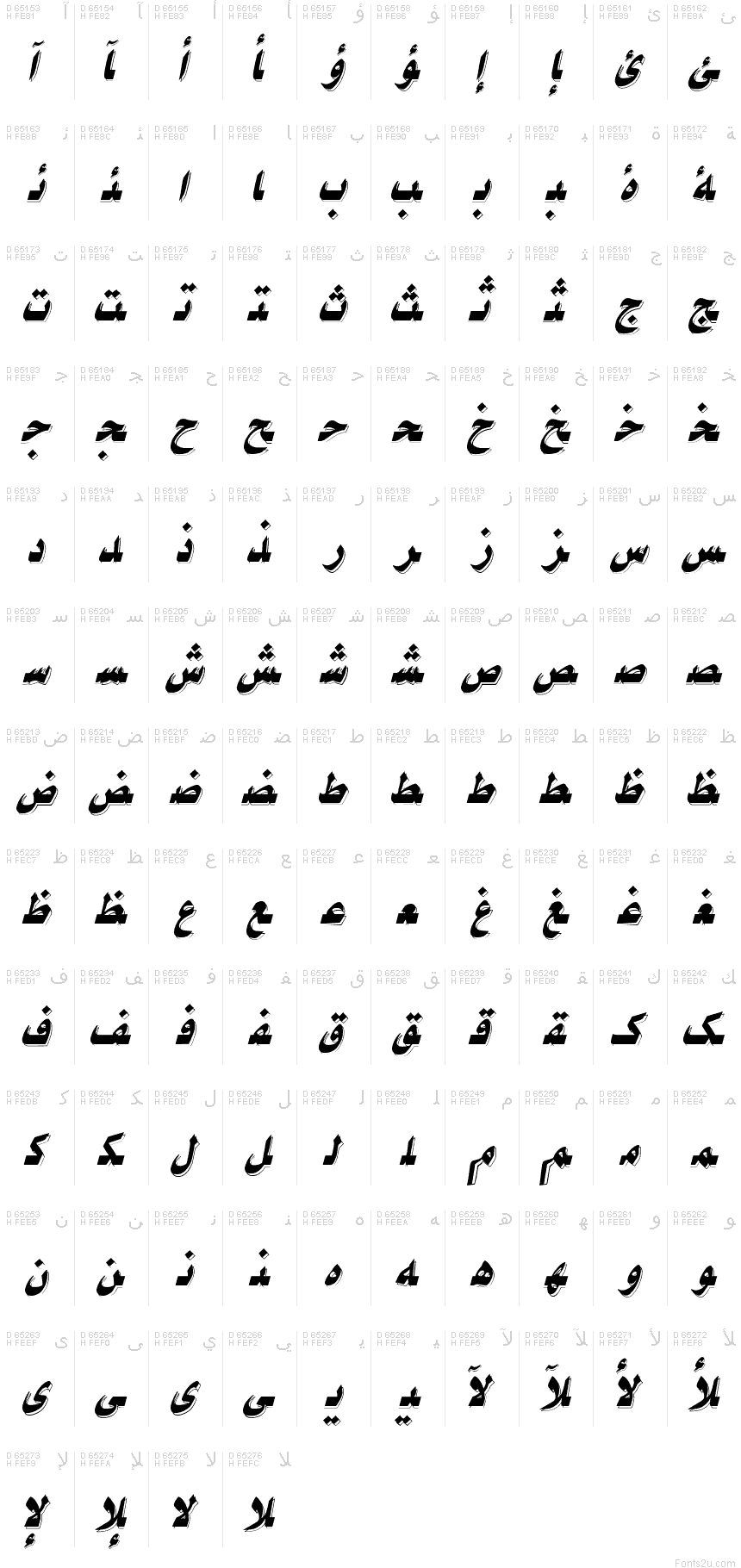
B Nikoo Italic autorstwa Borna Rayaneh to bezpłatny arabski font kursywny o płynnym, odręcznym charakterze. Litery łagodnie nachylają się ku sobie, tworząc miękkie, zaokrąglone kształty i zwężające się pociągnięcia, które nadają krojowi uprzejmy, konwersacyjny rytm, daleki od sztywności formalnej kaligrafii.
Dzięki temu ten darmowy font jest naturalnym wyborem do plakatów kulturalnych, okładek książek, opakowań, kartek okolicznościowych i krótkich nagłówków redakcyjnych, w których arabskie liternictwo powinno być pełne ciepła i delikatnego ruchu. Sprawdza się również w kartach tytułowych i projektach identyfikacji wizualnej, ponieważ ukośna, kursywna faktura nadaje nawet krótkim słowom wyrazisty, osobisty charakter.